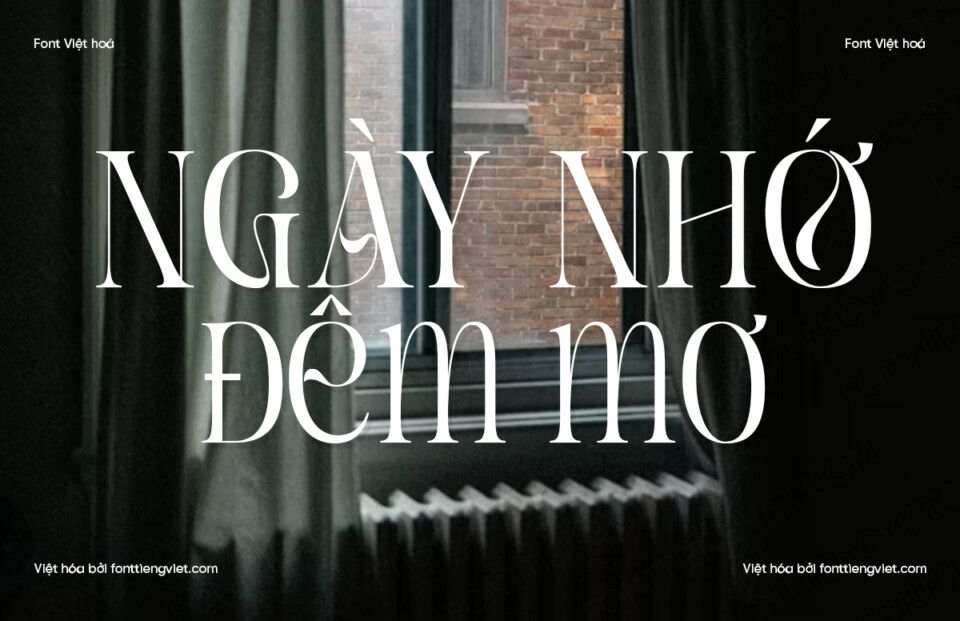
Font Việt hóa 1FTV VIP Argaka Fashion
Giới thiệu về sức hút của Font Việt hóa 1FTV VIP Argaka Fashion
Trong thế giới đồ họa hiện đại, việc lựa chọn một bộ Font Miễn Phí chất lượng luôn là ưu tiên hàng đầu của các nhà thiết kế chuyên nghiệp. Một trong những cái tên đang gây chú ý mạnh mẽ chính là Font Việt hóa 1FTV VIP Argaka Fashion. Đây là một bộ phông chữ mang đậm phong cách sang trọng, được lấy cảm hứng từ các tạp chí thời trang cao cấp và những sàn diễn danh giá trên thế giới. Khi được đội ngũ 1FTV tiến hành Việt hóa tỉ mỉ, bộ font này đã trở nên hoàn hảo hơn bao giờ hết cho người dùng tại Việt Nam, loại bỏ hoàn toàn các lỗi hiển thị dấu tiếng Việt gây khó chịu thường gặp ở những bản gốc tiếng Anh. Sự kết hợp giữa đường nét thanh mảnh và cấu trúc chữ hiện đại giúp nó trở thành công cụ đắc lực cho mọi dự án sáng tạo cần sự tinh tế.
Đặc điểm nổi bật của Font Việt hóa 1FTV VIP Argaka Fashion trong thiết kế
Phong cách Serif hiện đại và thời thượng
Điểm nhấn lớn nhất của Font Việt hóa 1FTV VIP Argaka Fashion chính là kiểu dáng Serif (có chân) nhưng lại không hề mang cảm giác cổ điển nặng nề. Thay vào đó, các nét chữ được tinh chỉnh để tạo ra sự thanh thoát, quý phái, phản ánh đúng tinh thần “Fashion” như chính tên gọi của nó. Những đường cong mềm mại phối hợp cùng các nét thẳng sắc sào tạo nên một tổng thể hài hòa, giúp các ấn phẩm thiết kế trở nên nổi bật và thu hút ánh nhìn ngay từ lần đầu tiên. Đây là lựa chọn tuyệt vời cho những ai đang tìm kiếm sự khác biệt trong tư duy hình ảnh.
Khả năng ứng dụng đa dạng trong nhiều lĩnh vực
Không chỉ giới hạn trong ngành thời trang, Font Việt hóa 1FTV VIP Argaka Fashion còn phát huy tác dụng cực tốt trong việc thiết kế logo thương hiệu, làm bìa sách, poster phim hay các thiệp mời sự kiện cao cấp. Đối với các bạn học sinh và sinh viên, bộ font này có thể dùng để làm đẹp cho các bài thuyết trình PowerPoint hoặc các dự án truyền thông học đường, giúp nội dung trở nên chuyên nghiệp và dễ tiếp cận hơn. Sự rõ ràng trong từng ký tự đảm bảo rằng dù bạn in ấn trên khổ lớn hay hiển thị trên màn hình điện thoại, thông điệp vẫn luôn được truyền tải một cách trọn vẹn và thẩm mỹ nhất.
Lợi ích khi sử dụng Font Việt hóa 1FTV VIP Argaka Fashion miễn phí
Việc sở hữu Font Việt hóa 1FTV VIP Argaka Fashion giúp các designer tiết kiệm rất nhiều thời gian trong khâu xử lý hậu kỳ. Bạn sẽ không còn phải tự mình vẽ thêm dấu hay điều chỉnh khoảng cách chữ thủ công, bởi mọi chi tiết đã được tối ưu hóa chuẩn xác theo bảng mã Unicode. Điều này cực kỳ quan trọng đối với các dự án có khối lượng văn bản lớn hoặc yêu cầu tiến độ nhanh. Hơn nữa, với văn phong giáo dục và sự phổ biến của cộng đồng thiết kế tại Việt Nam, việc học cách sử dụng và phối hợp bộ font này cũng trở nên đơn giản hơn với các tài liệu hướng dẫn phong phú.
Kết luận về bộ Font Việt hóa 1FTV VIP Argaka Fashion